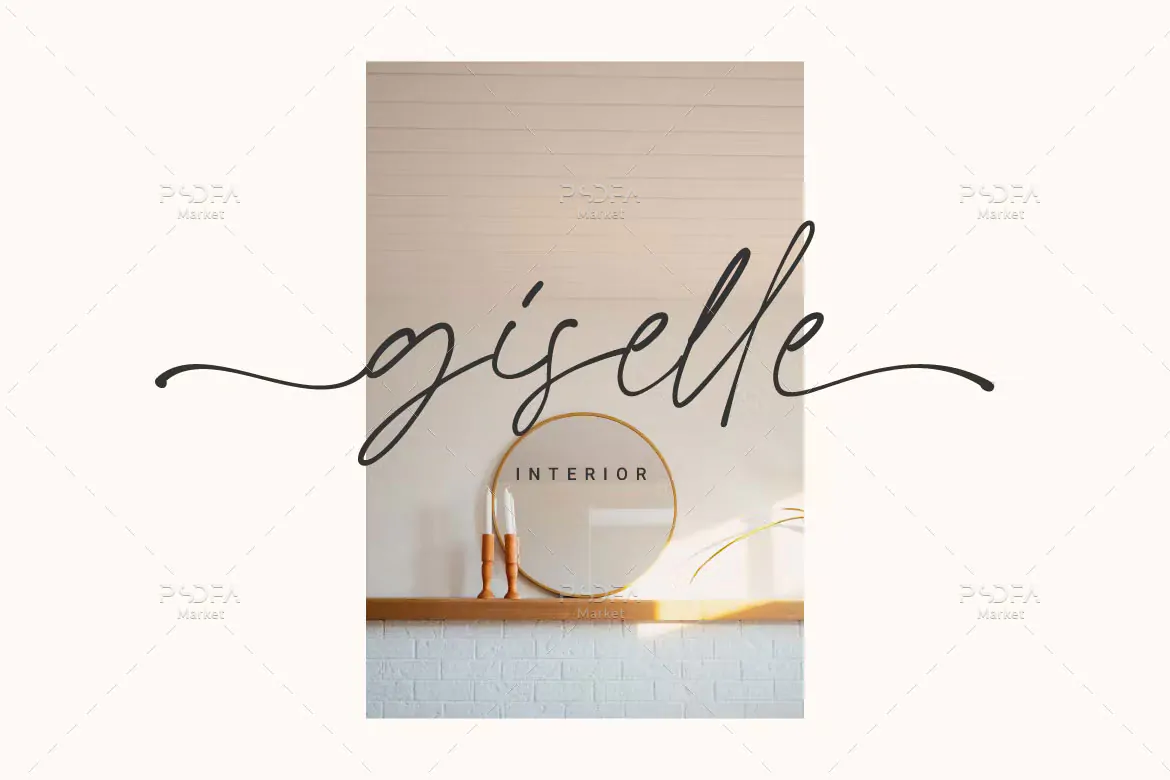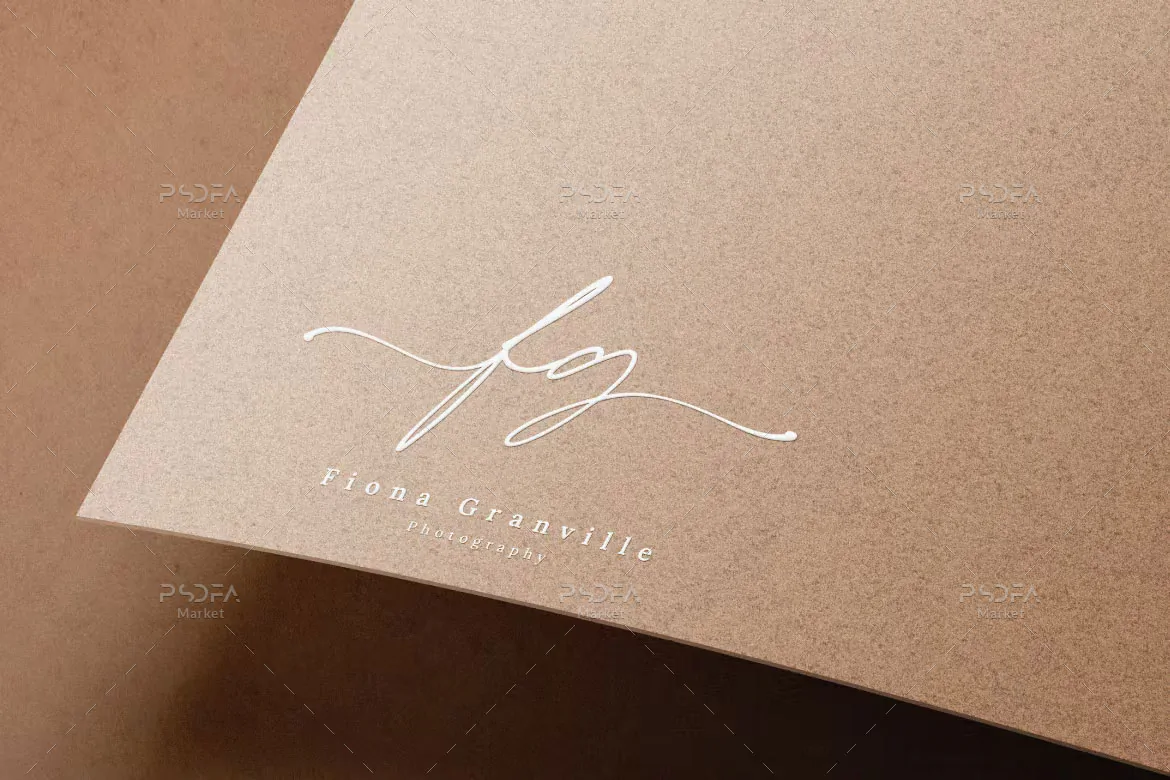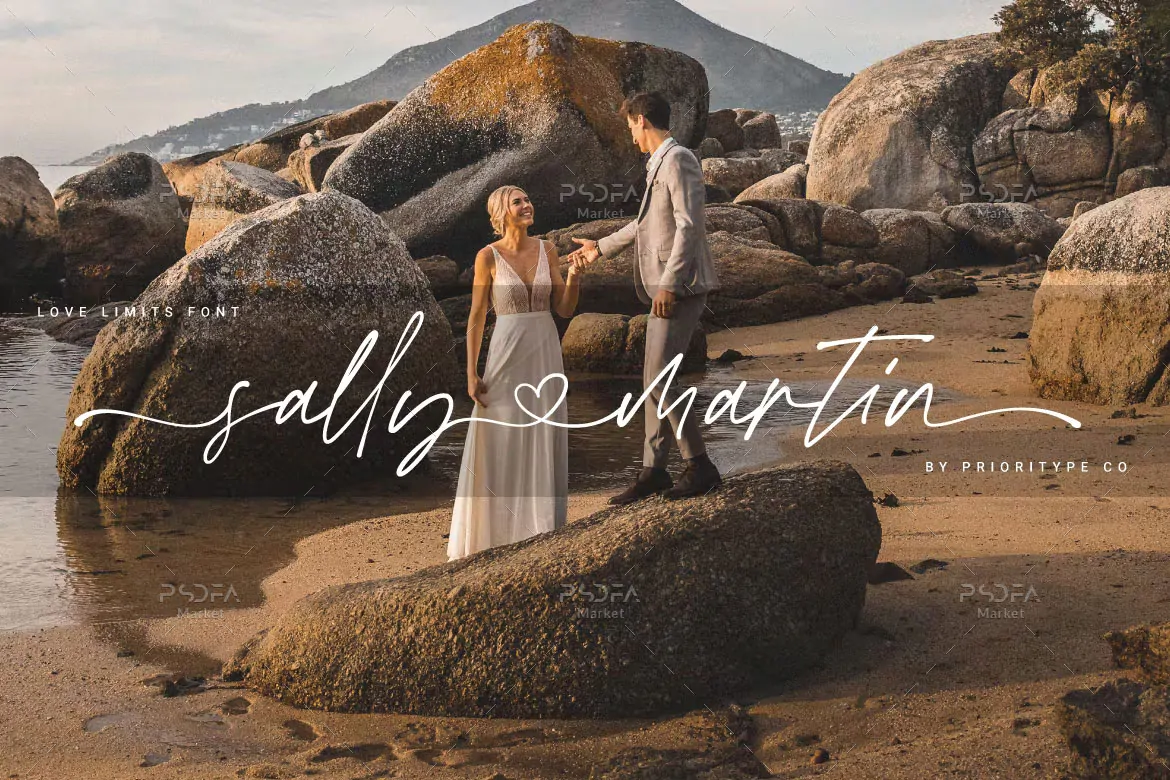
فونت سرهم رمانتیک و عاشقانه Love Limits
فونت سرهم رمانتیک و عاشقانه
فونت سرهم رمانتیک و عاشقانه Love Limits یک اسکریپت فونت دستنویس فوق العاده زیبا است که مناسب جهت استفاده در طرح و پروژههای گرافیکی مختلف میباشد. فونت Love Limits با وزن معمولی (Regular) طراحی شده است که میتوانید از آن در طراحی انواع پوستر، طرحهای رمانتیک و عاشقانه ولنتاین، کارتهای عروسی، کارت پستال، آرایشی و بهداشتی، جعبههای کادو و … استفاده کنید.